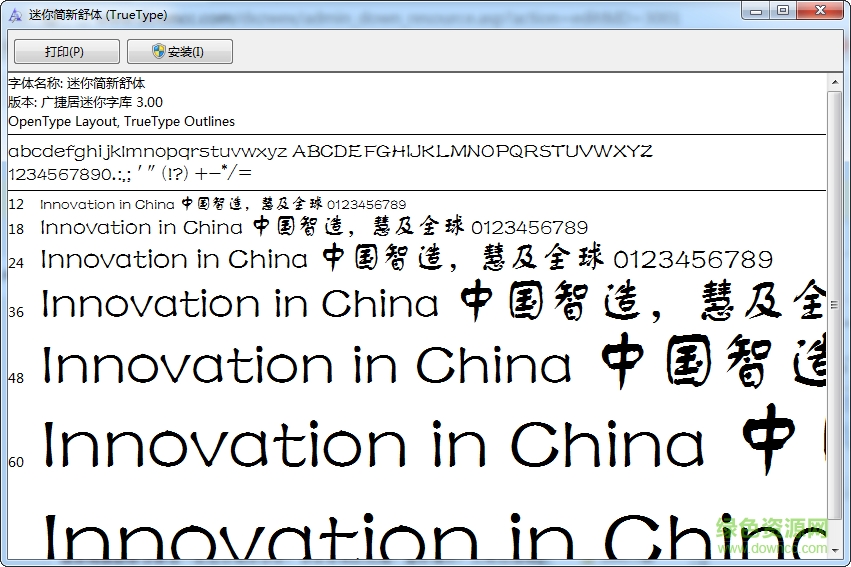
迷你簡(jiǎn)新舒體字體是一款迷你簡(jiǎn)體字體,字體非常的優(yōu)雅,整體偏長(zhǎng),又有點(diǎn)加粗的意味,祈禱了非常醒目的效果,非常適合廣告、報(bào)刊雜志等的印刷,喜愛(ài)的朋友趕快到綠色資源網(wǎng)下載體驗(yàn)吧!
字體樸實(shí)端正,筆法舒展有力,流暢自然,結(jié)構(gòu)勻稱,適
用于書、報(bào)、雜志和各級(jí)教材中的小標(biāo)題及正文字。
字形修長(zhǎng)秀美,平正端慶,線條婉轉(zhuǎn)流暢,骨力內(nèi)涵,
挺拔勁健,具有很高的實(shí)用性和欣賞性。該字體實(shí)用性
強(qiáng),注重篆法的正確和規(guī)范,注重字形美觀和風(fēng)格的統(tǒng)一。
其特點(diǎn)是端莊中含瀟灑,凝重中寓自然,字體簡(jiǎn)潔明快、
流暢大方、簡(jiǎn)繁齊備、雅俗共賞,更接近人們的生活,實(shí)
用性很強(qiáng),特別適用于書寫信函、報(bào)告、文章等。